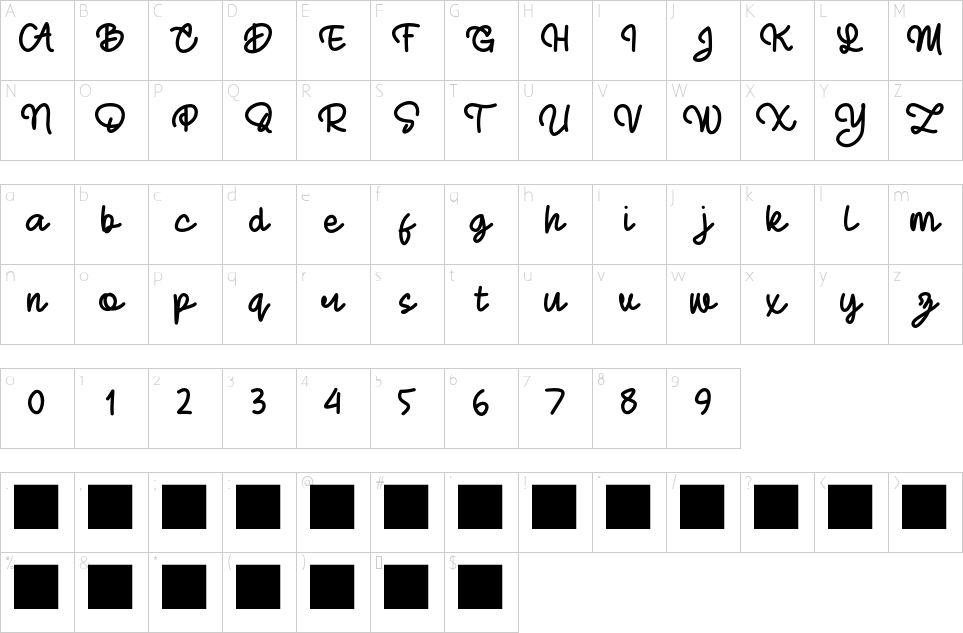
A fonte After Death é uma escolha inspiradora para quem busca um desenho único e moderno para seus projetos digitais. Ela foi projetada pela Intuisi Creative e tem sido baixada 1.054 vezes, evidenciando seu valor e popularidade. Esta fonte gráfica é perfeita para quem busca personalidade e estilo em suas criações, seja para assinatura de aplicativos, logotipos ou materiais de marketing digital. Com seu design inovador e moderno, After Death traz um toque único e moderno para qualquer projeto que você decida aplicar. Sua variedade de estilos torna-a versátil o suficiente para ser usada em diferentes aplicativos e ambientes gráficos. Com ela, você pode transformar qualquer design em um elemento que chamará a atenção e destacará sua marca. Sua disponibilidade tanto para Windows quanto para Mac torna After Death uma escolha versátil para qualquer criador digital.